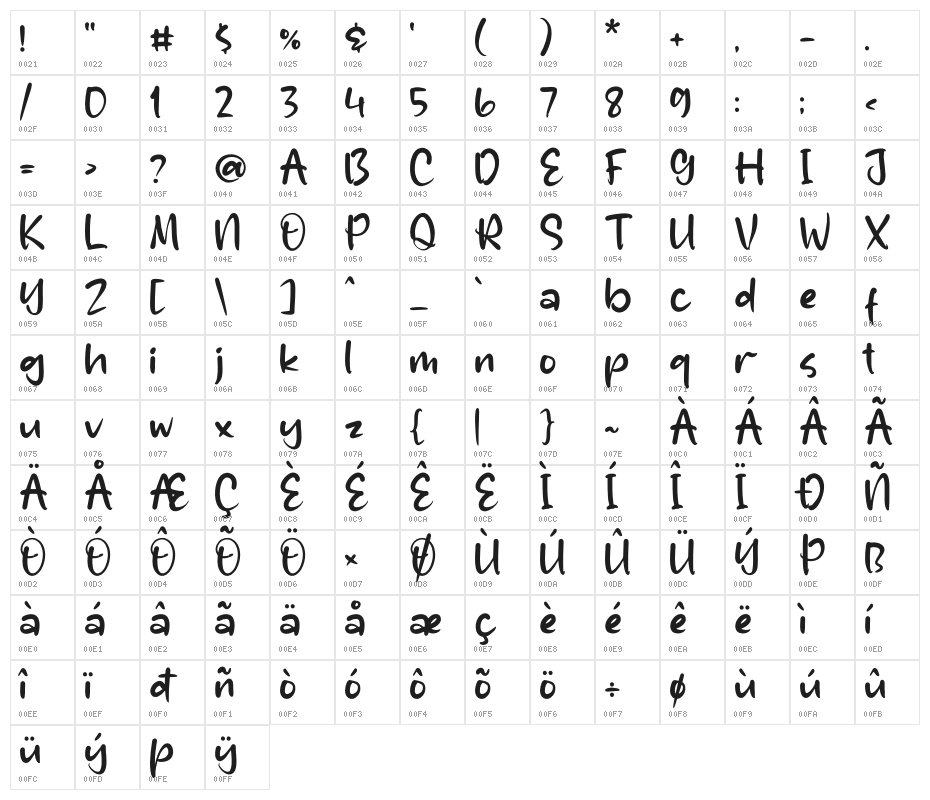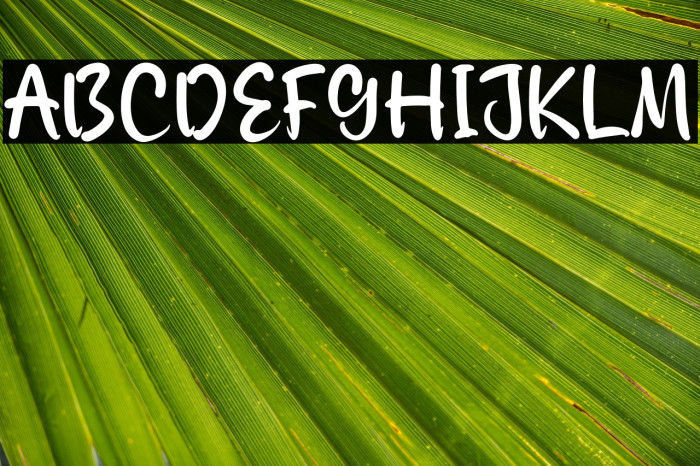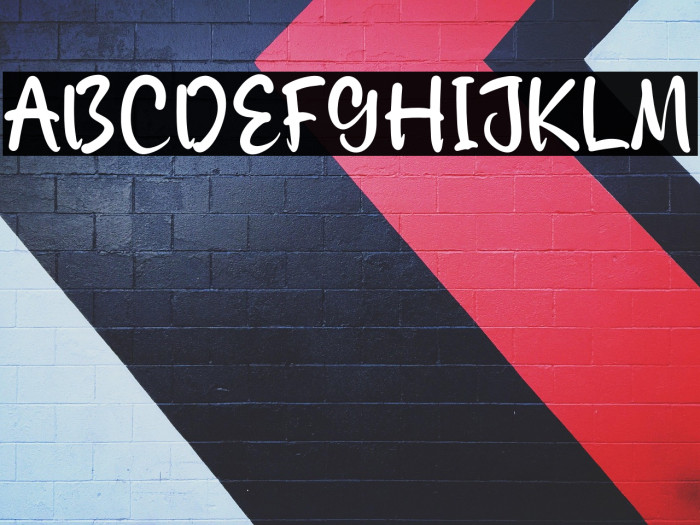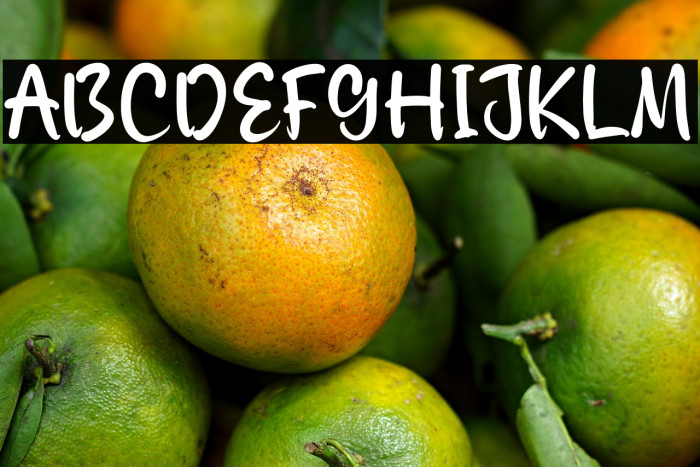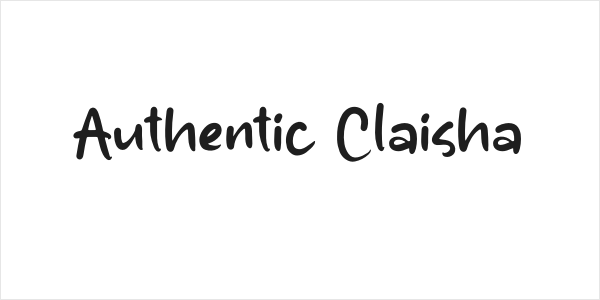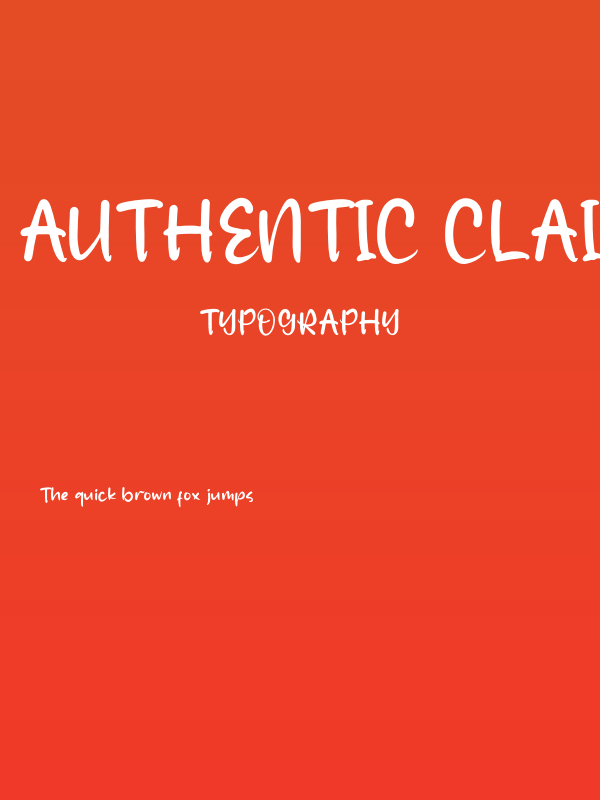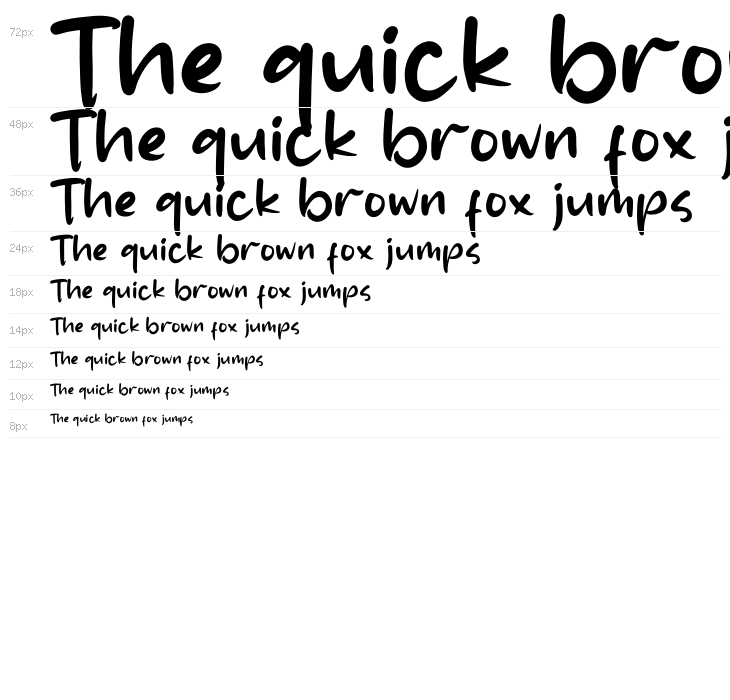
Authentic Claisha Font
| Gesamtstil | Playful, Energetic, Casual |
| Anwendungsfall | Headlines, Logos, Creative Projects |
| Vorgeschlagene Projekte | Ideal for greeting cards, children's books, playful branding, and creative social media graphics. |